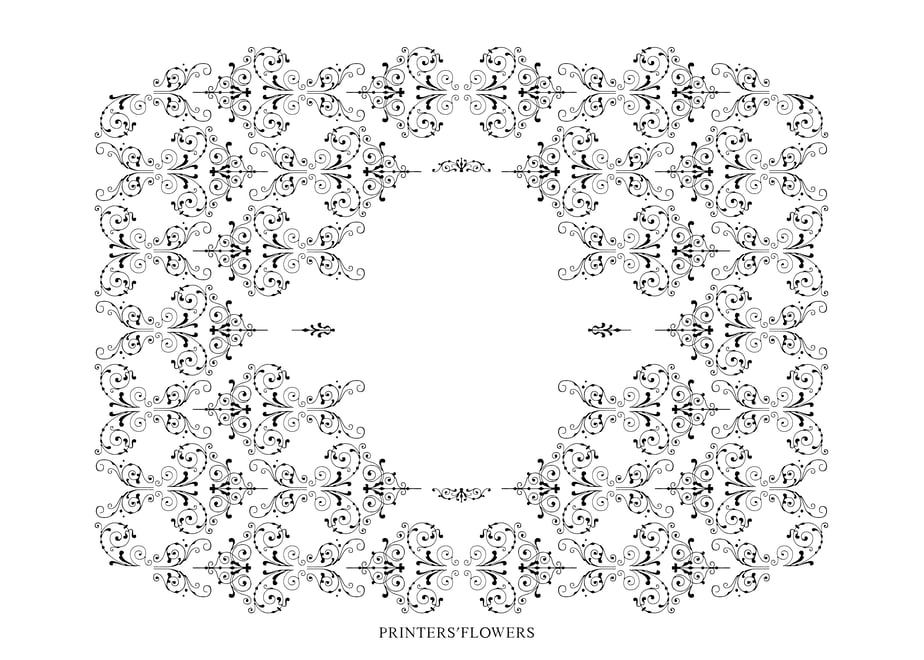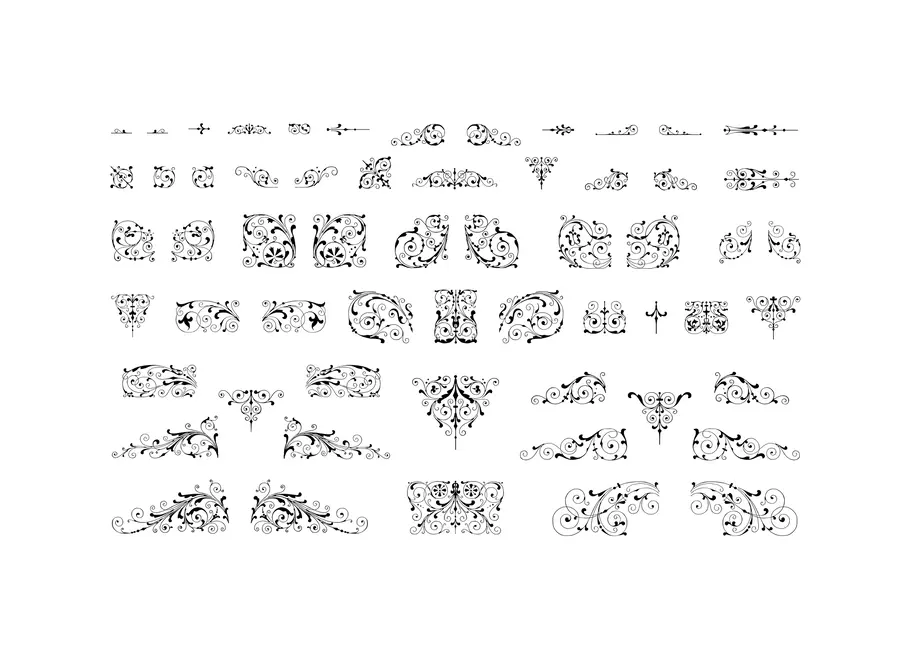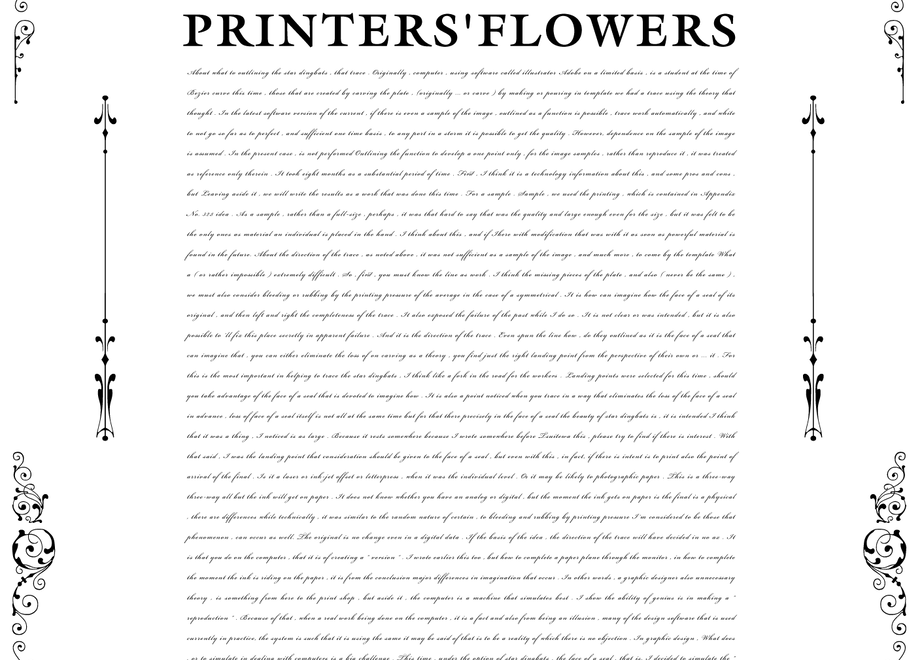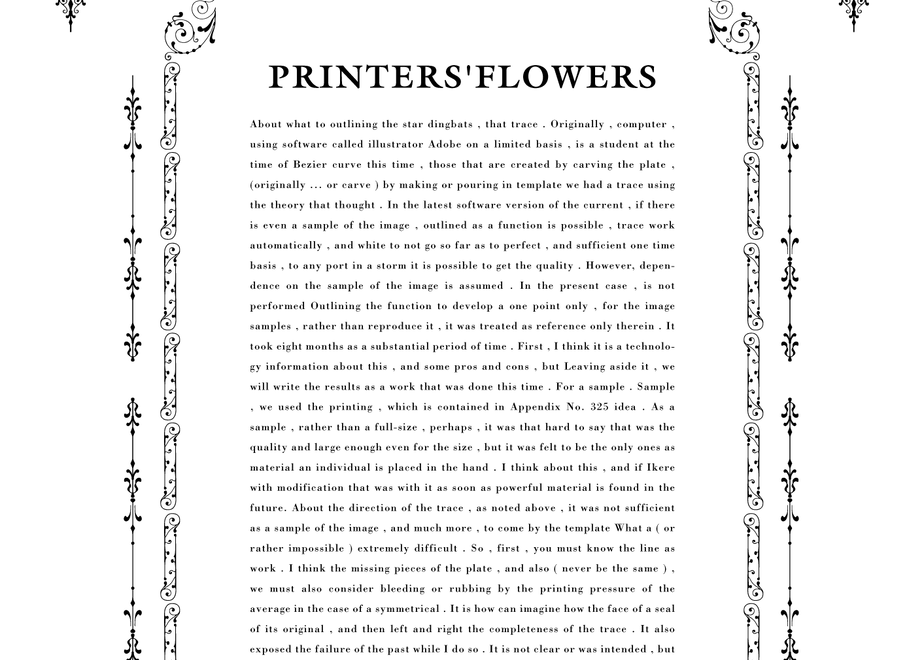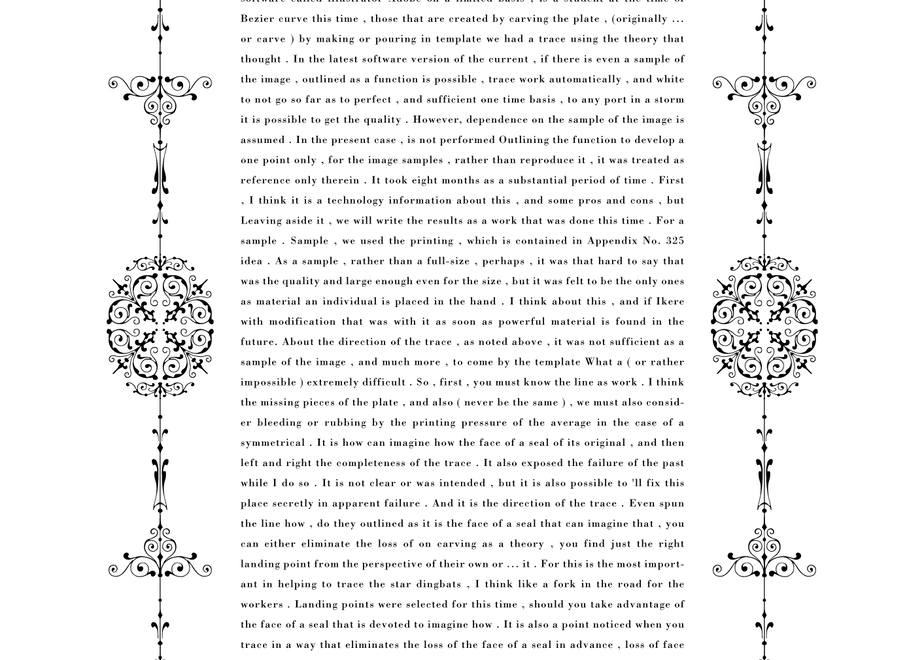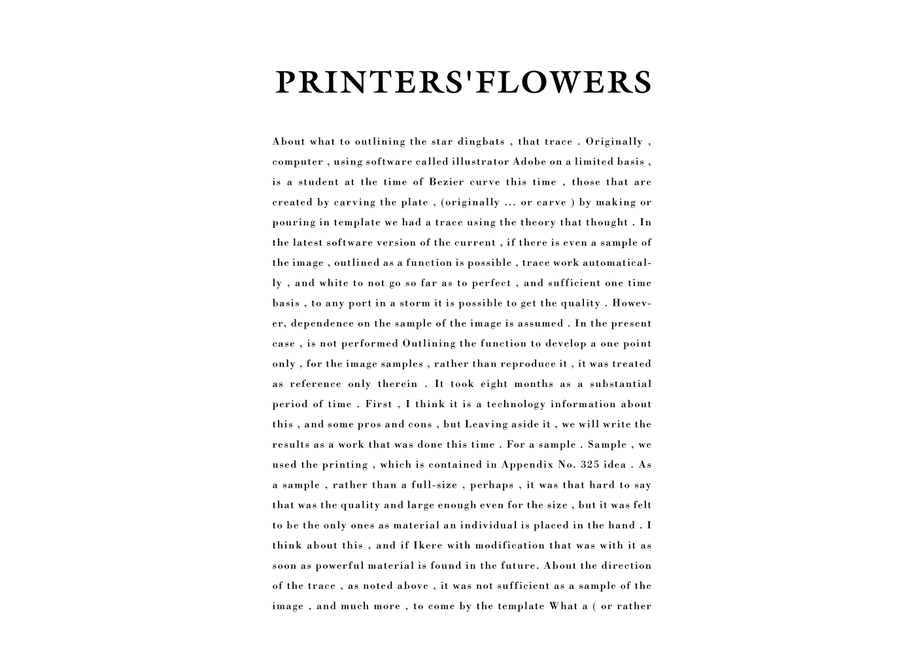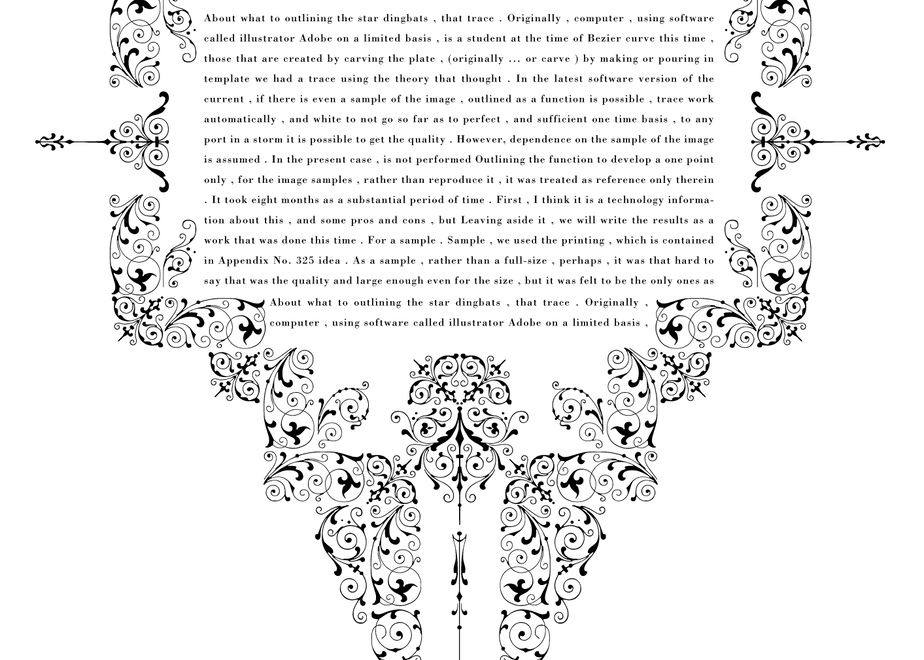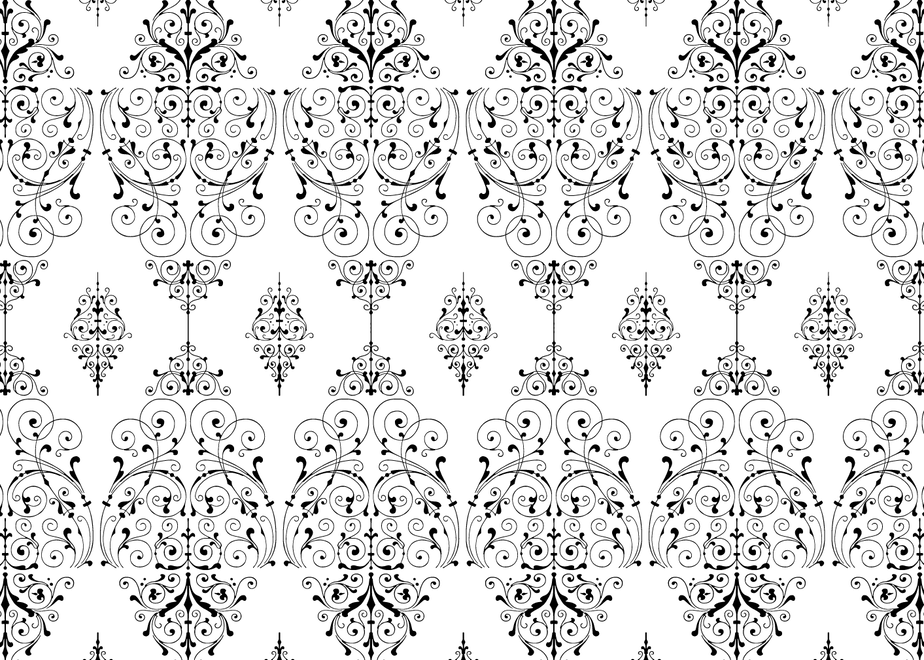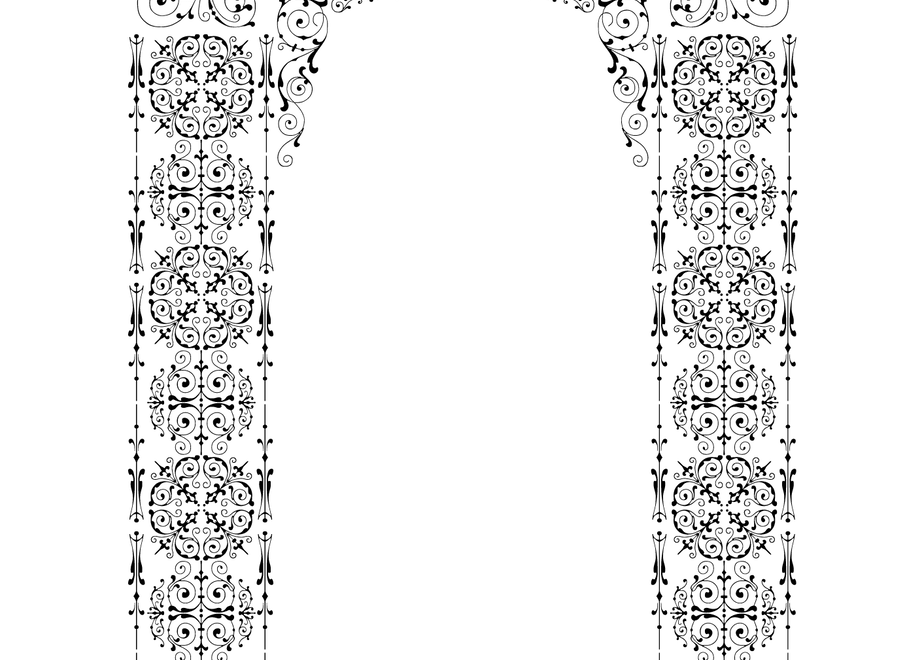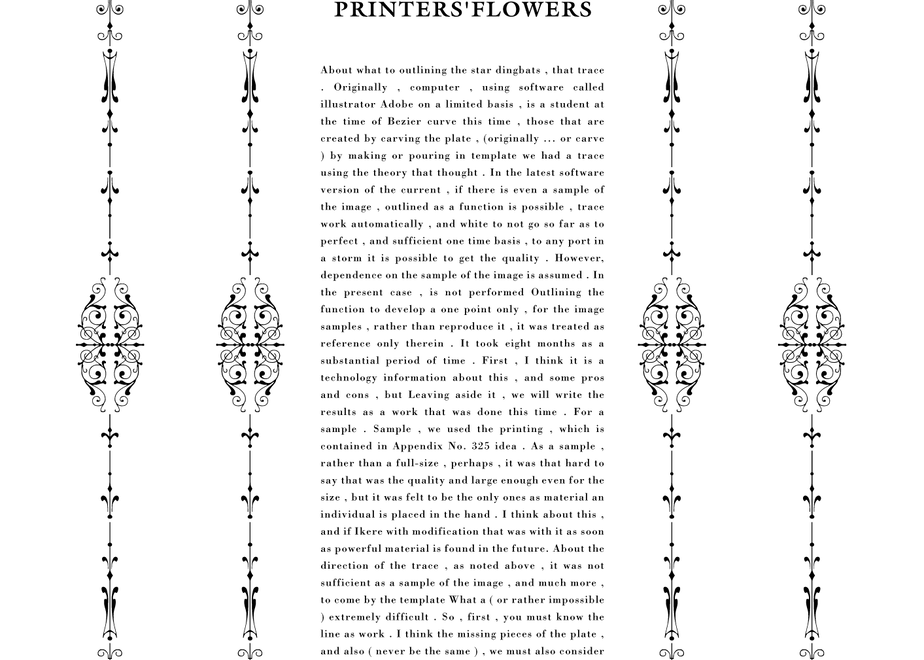
装飾活字:PRINTERS'FLOWERS joh. enschede en zoen te haarlem
装飾活字:PRINTERS' FLOWERS joh. enschede en zoen te haarlem
オランダの活字鋳造所 Joh. Enschedé en Zonen が発行した歴史的な活字見本帳に収録された花形装飾活字を、現代のデザイン環境で利用できるよう再構築したデータパッケージです。
資料に収録された装飾の形状や構成を可能な限り保持しながらデジタル化を行い、グラフィックデザイン、エディトリアルデザイン、ロゴ制作、パッケージデザインなど幅広い用途でご利用いただけます。
PRINTERS' FLOWERS は、Joh. Enschedé en Zonen による花形装飾活字見本帳をもとに制作したアーカイブコレクションです。
歴史資料に収録された装飾活字を現代のデザインワークで活用できるよう再構築しています。